Animography, tipografías con vida
Animography empezó en 2010 cuando Jeroen Krielaars, bajo el sobrenombre de Calango creo su primera tipografía animada Moshun, un proyecto personal de carácter experimental que tuvo repercusión en el mundo audiovisual después de aparecer destacado en un blog de Motionographer. Combinó con éxito una tipografía en movimiento dentro de un sistema modular. Poco tiempo después, otras plataformas online y revistas impresas también mostraron interés y recibió mucha atención de la prensa internacional.
La gran exposición del proyecto fue el motivo para explorar más el concepto de tipografías animadas y crear una plataforma para artistas. Diseñadores gráficos, programadores y animadores de diferentes ramas mostraron interés por las tipografías animadas y unieron fuerzas para crear Animography. Un lugar para la colaboración, la experimentación y por supuesto la venta de archivos tipográficos y herramientas para After Effects. Una plataforma y tienda web que crea tipografías animadas, personalizables y fáciles de usar.
El crecimiento de la plataforma inicialmente fue por invitación y cooperación entre diseñadores fruto de la combinación de talentos interdisciplinarios. Hoy se ha convertido en un espacio de experimentación e implementación tipográfica de infinitos parámetros gráficos. De esa manera nació un proyecto paralelo llamado Animography Monthly, que invita a diseñadores de Motion Design a trabajar con una tipografía de su elección para animarla con su estilo. Los resultados tipográficos son sorprendentes y es muy interesante ver el proceso de creación solamente para observar como cada animador convierte una tipografía en algo nunca visto hasta ahora.
El proceso de creación de una tipografía animable está construida en Adobe After Effects, es customizable y muy intuitiva de usar. Cada letra está animada individualmente para que aparezca, se mantenga, se repita y desaparezca. El usuario puede escribir, manipular el interletraje, poner tildes, puntuaciones, utilizar varios pesos, etc. con un sistema muy parecido a cualquier otro tipo de letra, pero con una dimensión extra, el tiempo. Las tipografías animadas vienen con un controlador que permite configurar el ancho de línea, múltiples colores, aleatoriedad de caracteres, velocidad de movimiento e incluso sonidos adicionales que se pueden activar y desactivar.
Las tipografías animadas, posiblemente legado de las animaciones cinéticas, se han vuelto en los últimos años más accesibles en todo tipo de plataformas digitales y, como consecuencia de esto, se ha generado una especialización dentro del Motion Design. Repasamos las tipografías de Animography, que a mi parecer, son una combinación perfecta entre diseño y animación.
Franchise
Es una tipografía animada por 110 animadores talentosos de todo el mundo. Todos los animadores eligieron un glifo tipográfico y tuvieron que animarlo usando no más de 4 colores, 25 fotogramas por segundo y un lienzo de 500px x 600px en Adobe After Effects. Los animadores tuvieron total libertad para desarrollar su trabajo dentro de estos parámetros. El resultado es una amplia variedad de estilos y técnicas unido por una misma paleta cromática.
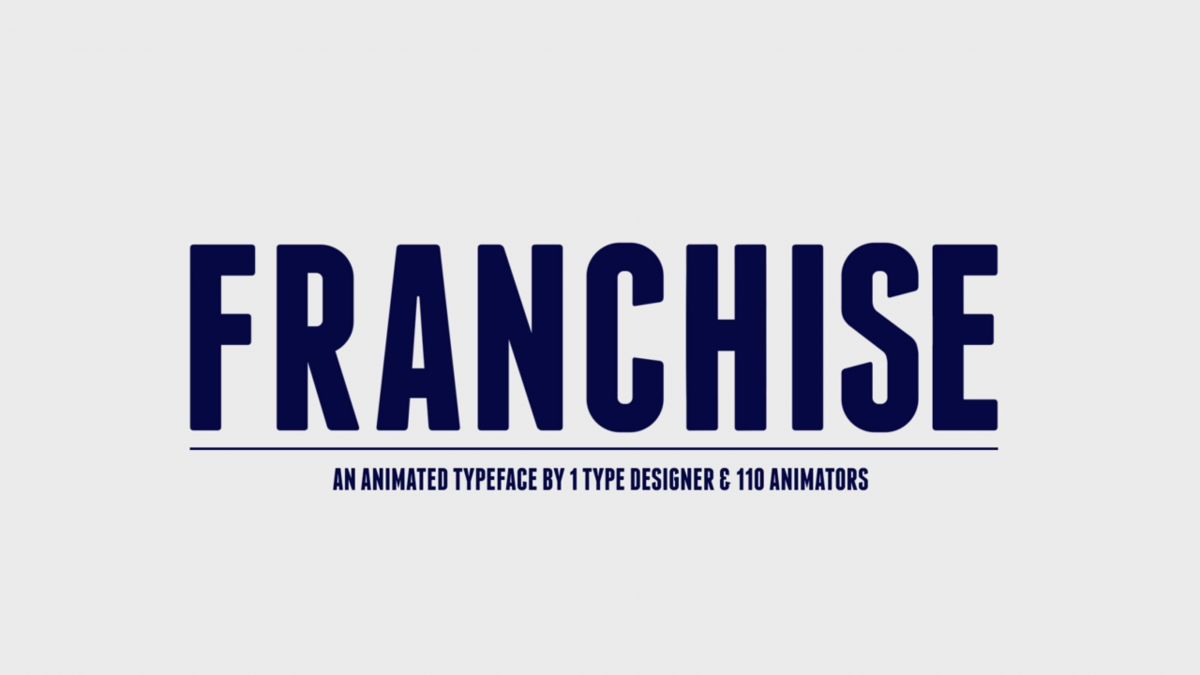
Utopian
Es una tipografía diseñada por Alex Trochut y animada por Pablo Lozano, influenciada por el trabajo de Mondrian, Sol Lewitt y De Stijl. Una tipografía modular muy gráfica con animaciones a juego con el estilo. Los adornos se mantienen al mínimo y el enfoque se centra en las formas primarias. Cada carácter se construye a partir de una forma rectangular que complementa la simplicidad de las letras, al tiempo que brinda formas interesantes y revela cada glifo tipográfico.
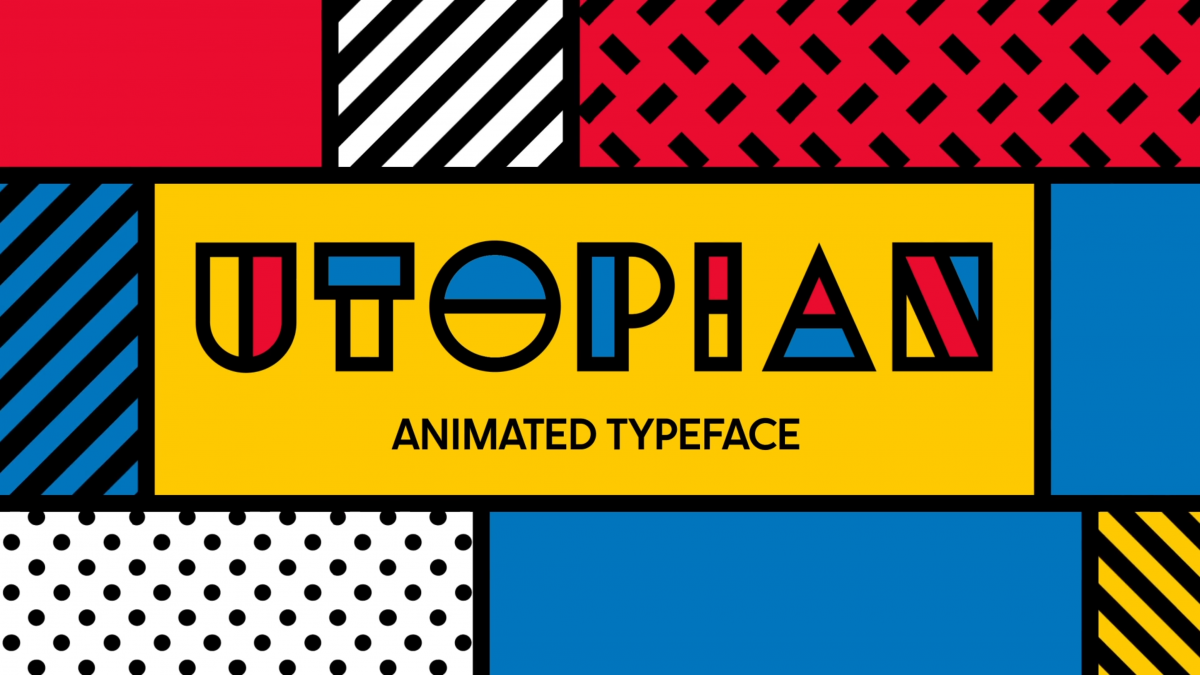
Colloid
Tipografía con animaciones cuidadosamente realizadas fotograma a fotograma. Cada letra se forma a partir de una danza entre dos líquidos de colores. El movimiento dibujado a mano proporciona infinidad de detalles y matices. Debido a que la duración de cada letra es diferente, siempre terminas con un flujo diferente que aporta dinámico. Toda la animación se crea en vector y es escalable a cualquier tamaño sin pérdida de calidad.